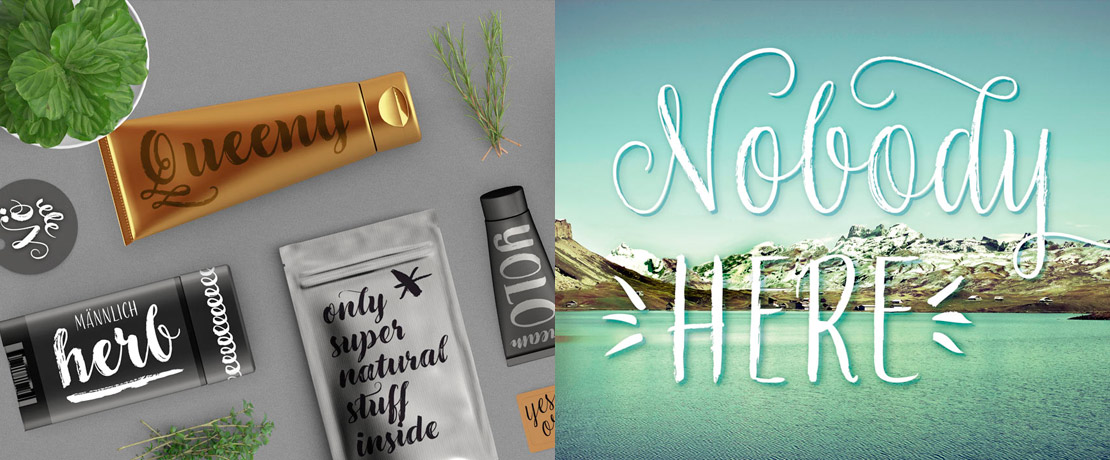
»LiebeGerda« ist da
Die Berliner Typedesignerin Ulrike Rausch hat nach fast einem Jahr Arbeit die Pinselschrift »LiebeGerda« veröffentlicht. Die Schnitte sind komplett von Hand geschrieben. Alle Buchstaben weisen mehrere Varianten auf.
Durch die Nutzung von OpenType-Features lassen sich die Buchstaben automatisch durchmischen. 1.200 Zeichen sind enthalten. Diese sorgen für Abwechslung im Schriftbild und unterstreichen den handgeschriebenen Charakter.
Im Paket von »LiebeGerda« sind vier Fonts enthalten, die unterschiedlich aussehen, aufeinander abgestimmt sind und sich munter kombinieren lassen. Auf der Website von LiebeFonts lassen sich die Schnitte direkt auf dem Bildschirm ausprobieren.